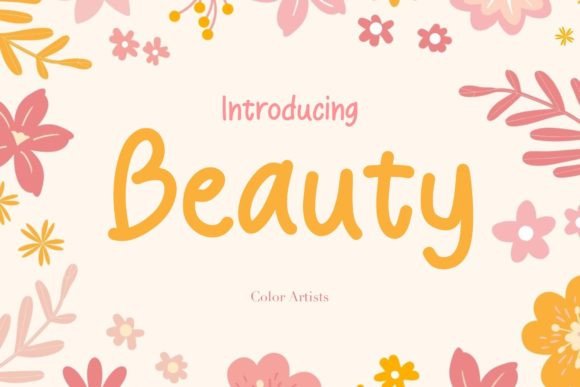
Beauty
إذا كنت تبحث عن أصول عالية الجودة مثل Beauty، فإن هذه الحزمة المميزة هي خيار رائع لمشاريعك الإبداعية.
تم تصميمه بدقة، ويوفر Beauty متجهات نظيفة وطباعة سلسة وترخيصًا تجاريًا لراحة بالك.
سواء كنت تقوم بإنشاء منتجات الطباعة عند الطلب أو دعوات الزفاف أو رسومات وسائل التواصل الاجتماعي، فإن Beauty هو الخيار المثالي.